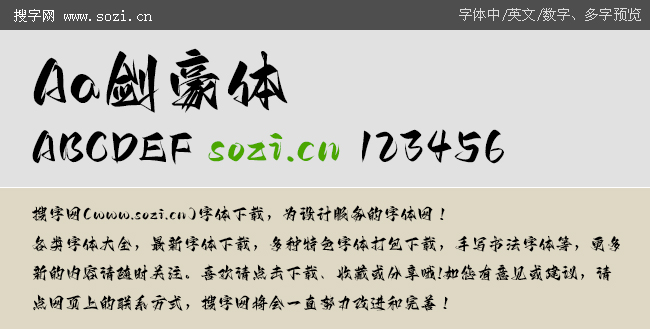
Aa劍豪體
搜字網(wǎng)給大家提供一款A(yù)a劍豪體(非商業(yè)使用)中文字體下載,Aa劍豪體是一款手寫書法字體,字體一筆一劃鋒芒畢露,豪放灑脫,極具張力,個性十足。適合應(yīng)用于藝術(shù)設(shè)計、平面宣傳設(shè)計、網(wǎng)頁設(shè)計、海報設(shè)計等應(yīng)用(此字體為個人非商用版,商用可以聯(lián)系QQ:1006760504)。